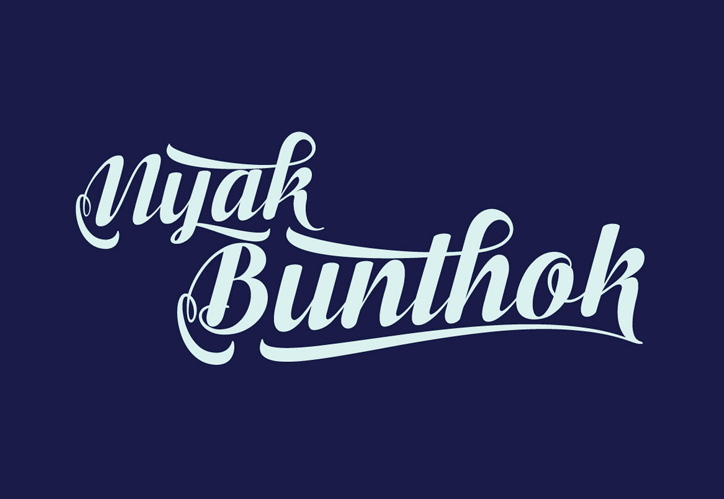
Bunthok Script Font – Download Grátis
Introduzimos a Bunthok Script, uma fonte de escrita clássica. Esta nova fonte script traz um estilo moderno e fresco, com personagens decorativos e uma linha base que dança. É absolutamente encantadora para aplicações como convites, cartas de cumprimento, materiais de marca, cartões de visita, citações e posters. A sua elegância e sofisticação torna a Bunthok Script uma escolha inegável para qualquer projeto gráfico que deseja destacar-se. Seja ela o seu selo de qualidade em um convite personalizado ou o texto de destaque num poster publicitário, a Bunthok Script é perfeita para deixar marcas duradouras.